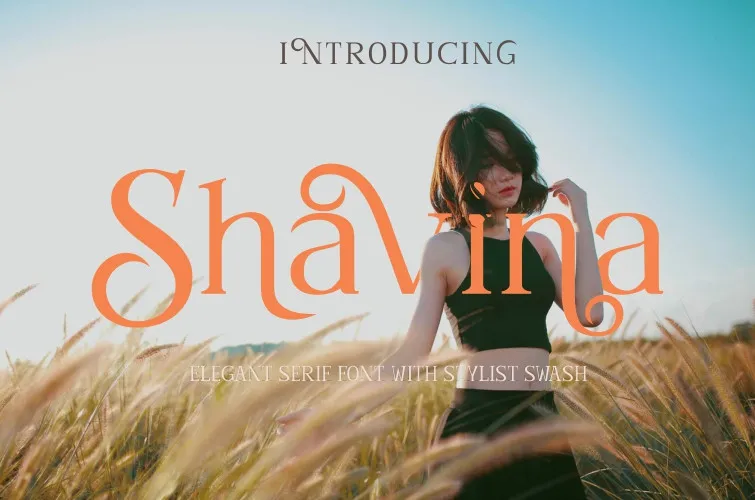
Shavina Serif Font – Fonte Grátis
Shavina Serif Font
A Shavina Serif é uma fonte elaborada com conceitos elegantes e femininos, trazendo curvas decorativas que se tornam alternativas perfeitas para aplicações como logotipos, textos de citação e projetos visuais focados em produtos de beleza ou propriedades requintadas. Suas curvas fluidas e suaves a tornam uma opção ideal não apenas para design de logotipo mas também para qualquer tipo de aplicação textual que exige um toque elegante. Com seus traços delicados, a Shavina Serif é perfeita para destacar mensagens importantes em uma tipografia elegante e sofisticada, fazendo com que sua beleza se destaque em designs variados. A fonte incorpora várias características de design que permitem uma variação impressionante na forma como ela aparece em diferentes texturas e tamanhos, tornando-a uma escolha versátil para designers profissionais.